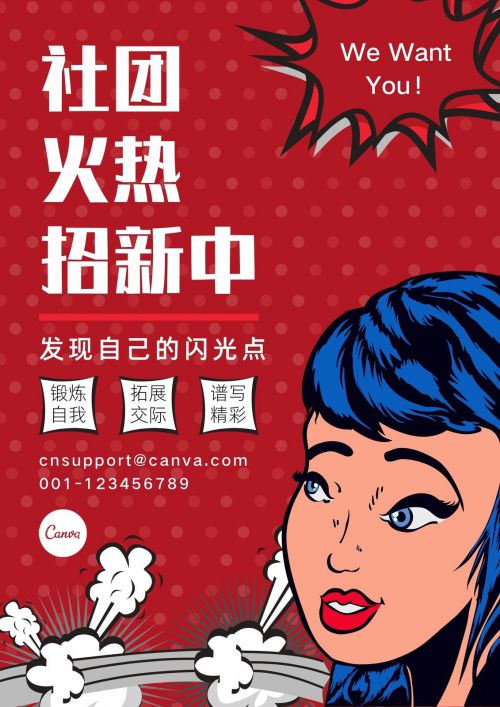
阿里汉仪智能黑体
字库品牌: 汉仪字库 >
阿里汉仪智能黑体是一款智能字体设计,在传统的黑体基础上加入了智能化元素,使其更加灵活和多样化。阿里汉仪智能黑体具有智能化的特点,可以自适应调整,能够呈现出最佳的视觉效果,提供更好的阅读和浏览体验。阿里汉仪智能黑体具有良好的可读性和适应性,字体设计风格独特,但形状仍然清晰可辨。无论是标题、标志、海报还是印刷品,都能够展现出其独特的魅力。